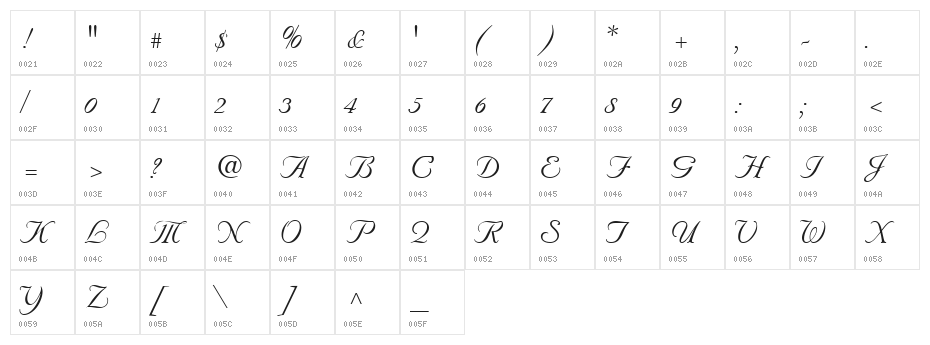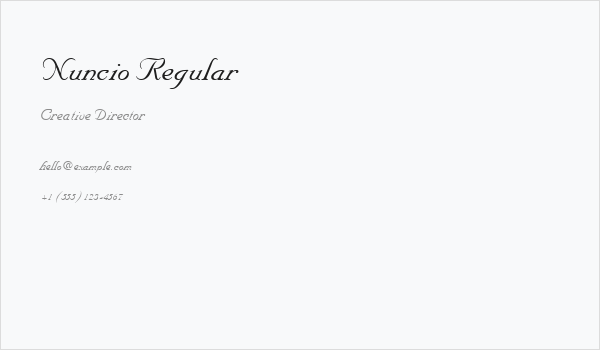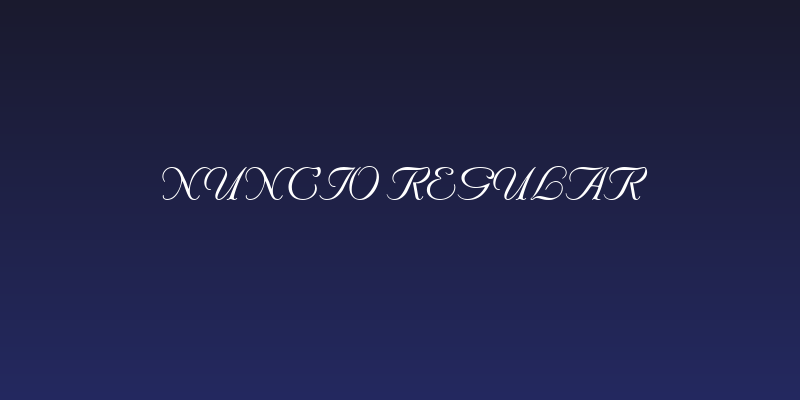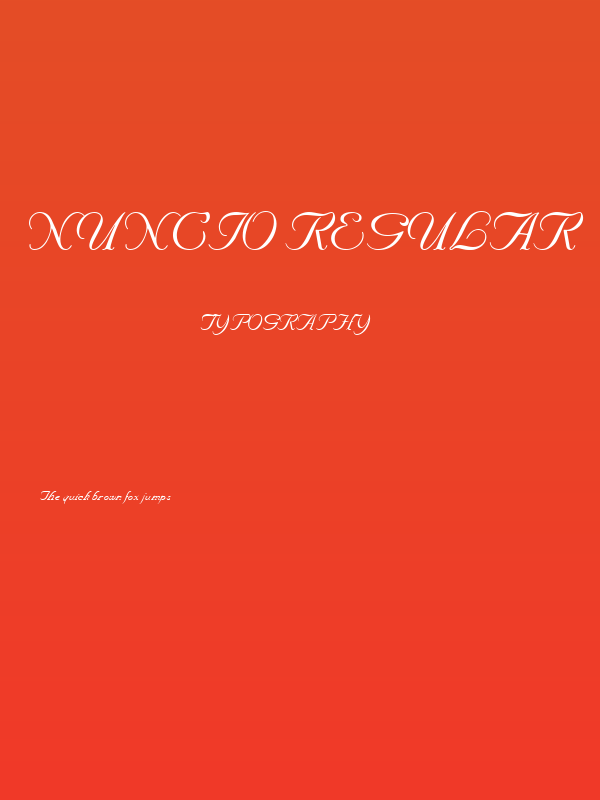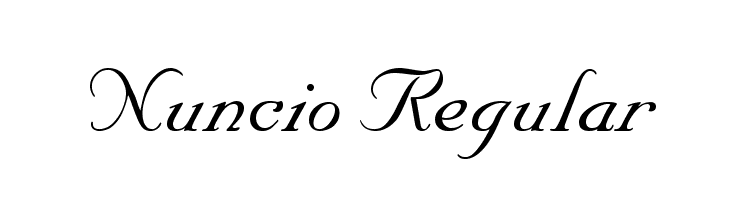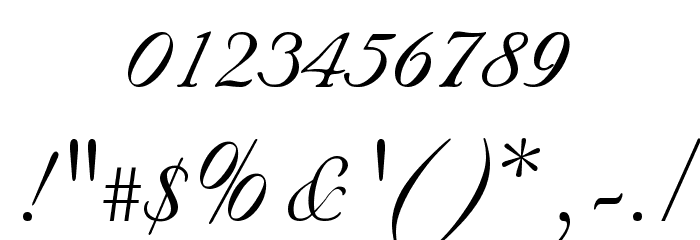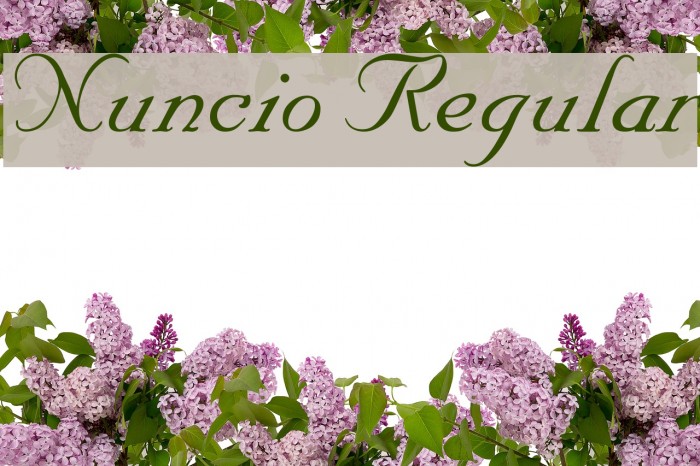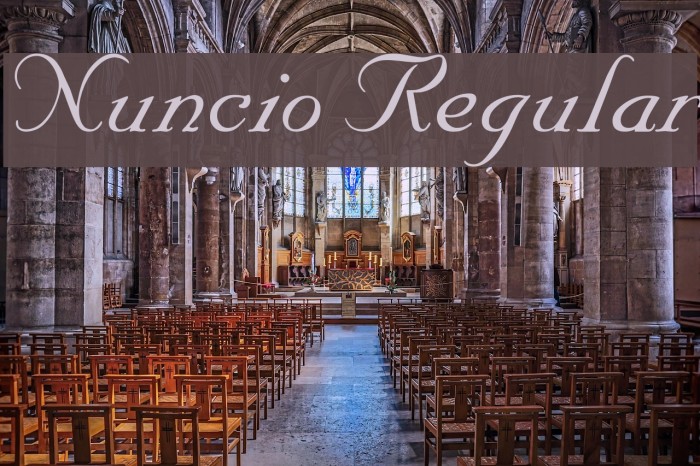
Nuncio Regular Font
| مائل | Yes |
| النمط العام | Classic |
| حالة الاستخدام | Logos, Invitations, Branding |
| مشاريع مقترحة | Ideal for wedding invitations, luxury branding, formal event programs, and elegant packaging designs. |